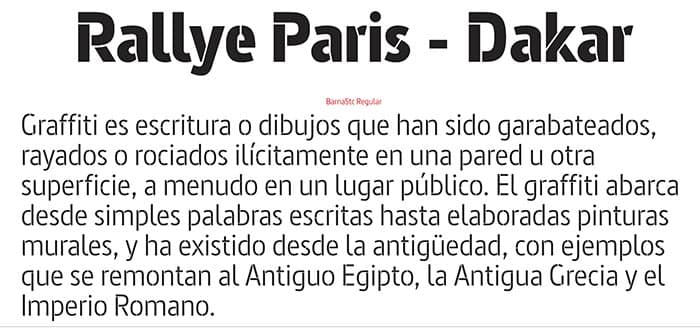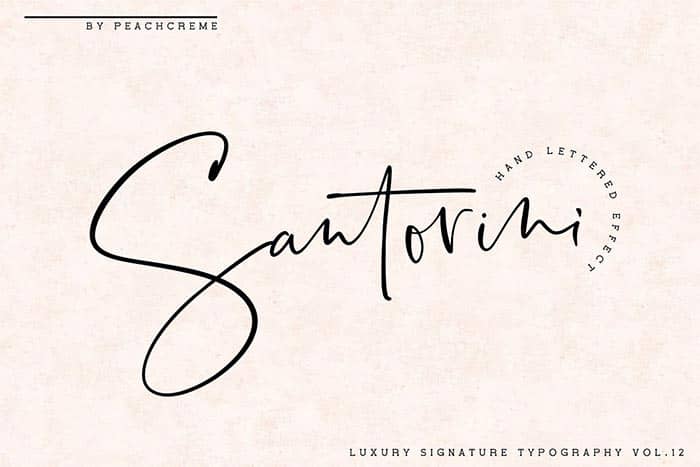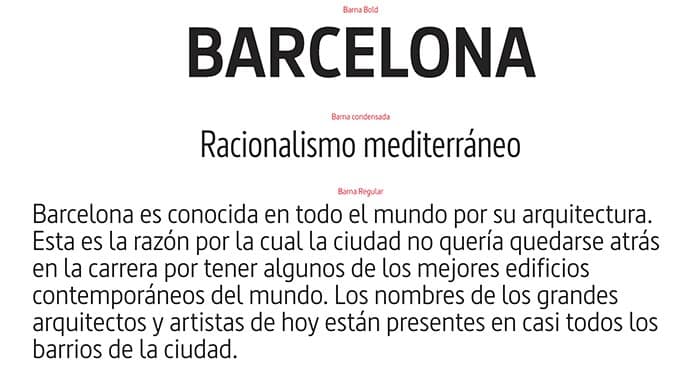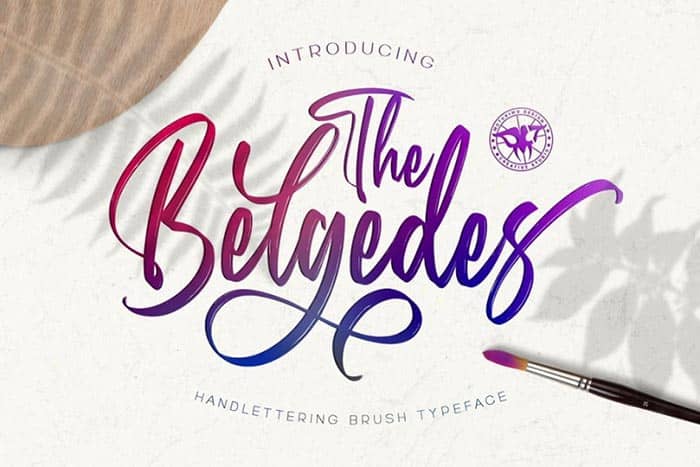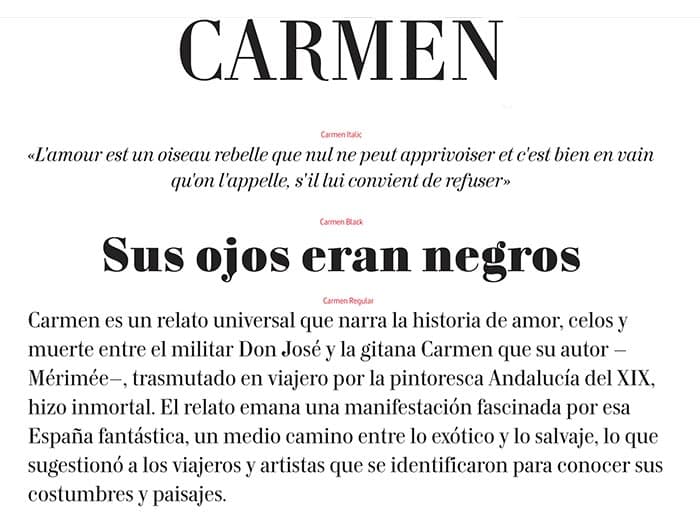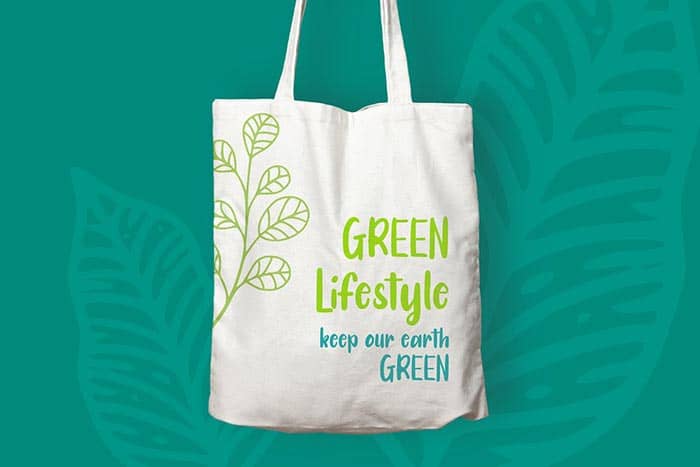
Tipografía moderna
En este caso me encontré no con dos tipografías sino con dos nuevas formas de ver fonts, dos nuevos e interesantes vertientes, decir también que no a cambiado la clasificación tipográfica clásica, creo seriamente que a cambiado la forma de ver la tipografía, además de dar un mensaje que leemos, da un mensaje estético que en momento es superador al que leemos.
Si buscas bien en este blog, hay algo de tipografía, tal vez no demasiada, pero sí interesante, como los clásicos Helvetica, Frutiger, Caslon etc,. Hoy veremos algo de tipografía moderna.
En este caso me encontré, no con dos tipografías, sino con dos nuevas formas de ver fonts, dos nuevos e interesantes vertientes. Hay que decir también que no ha cambiado la clasificación tipográfica clásica, en su lugar ha cambiado la forma de ver la tipografía. Además de dar un mensaje que leemos, da un mensaje estético que por momentos es superior al que leemos.
Lettering forma parte de la tipografía moderna. Se trata de leer, comunicar, flotar y divertirse usando bellos tipos manuscritos, como Belgedes Script Brush, Luxury Signature, Alenka. A esta y otras más las podemos ver en GDJ graphic, templo del diseño moderno.
Aquí cambia el estilo de diseño. En este intentan mostrar otra estética. Estas fonts tienen que ver con diseños algo más tradicionales, pero a la vez modernos, actuales, llevando a la tipografía a la calle, a los anuncios en vía pública, a identificar ese font con una marca. Este tipo de fonts las encontré en un sitio llamado type republico.